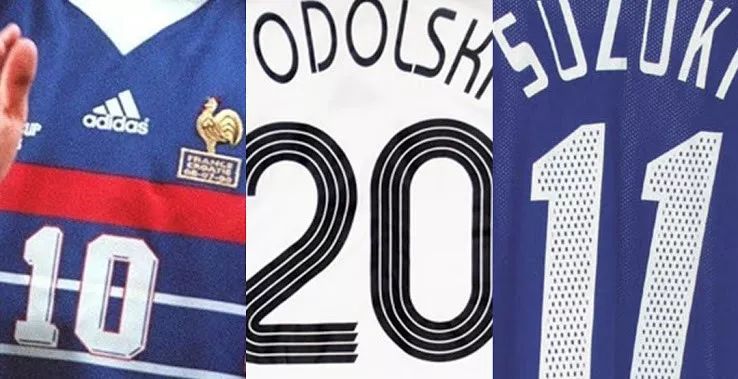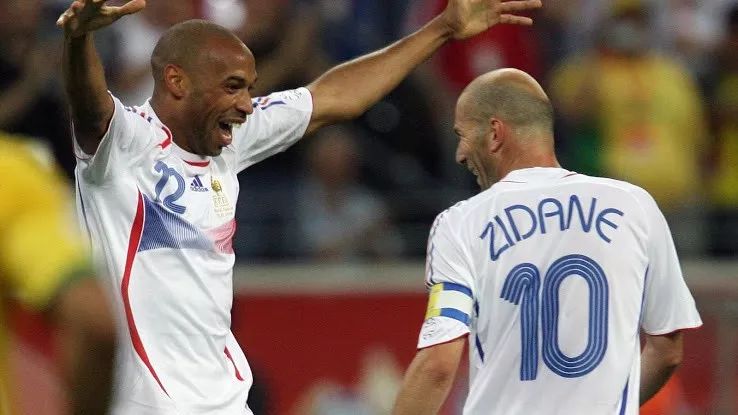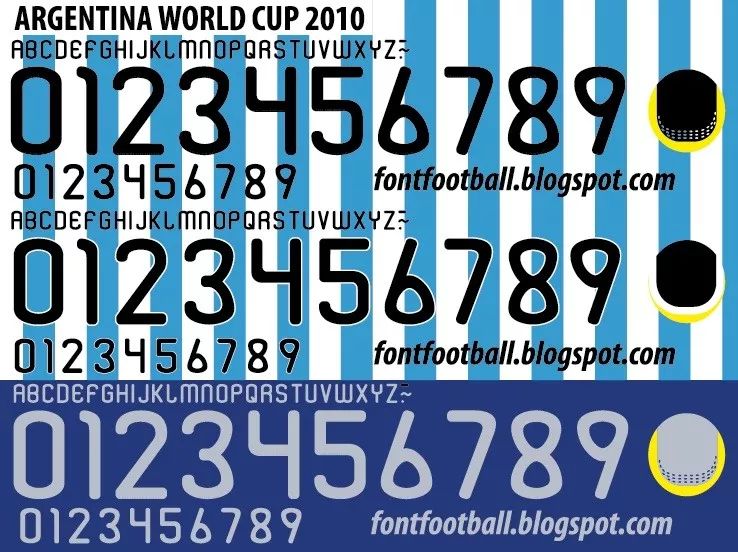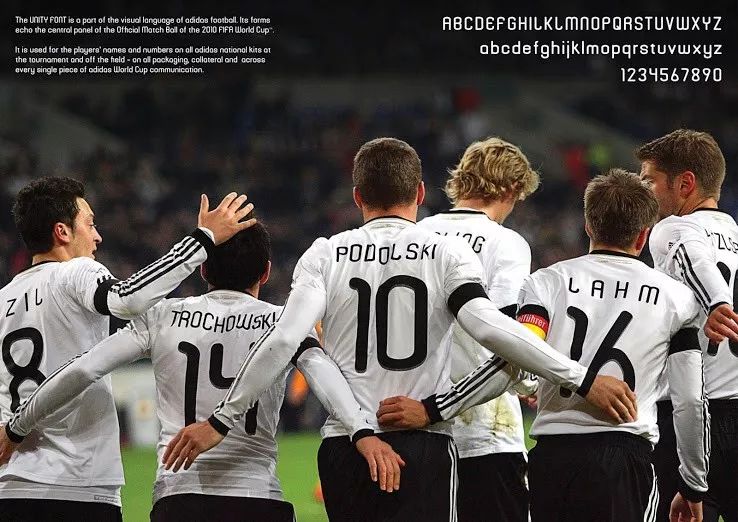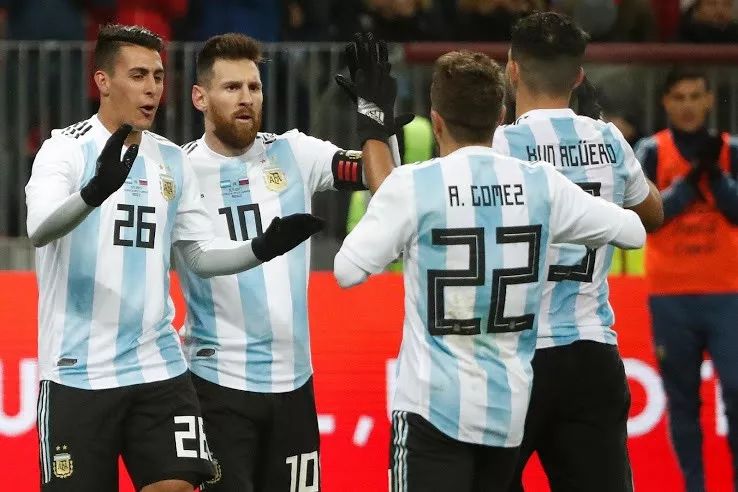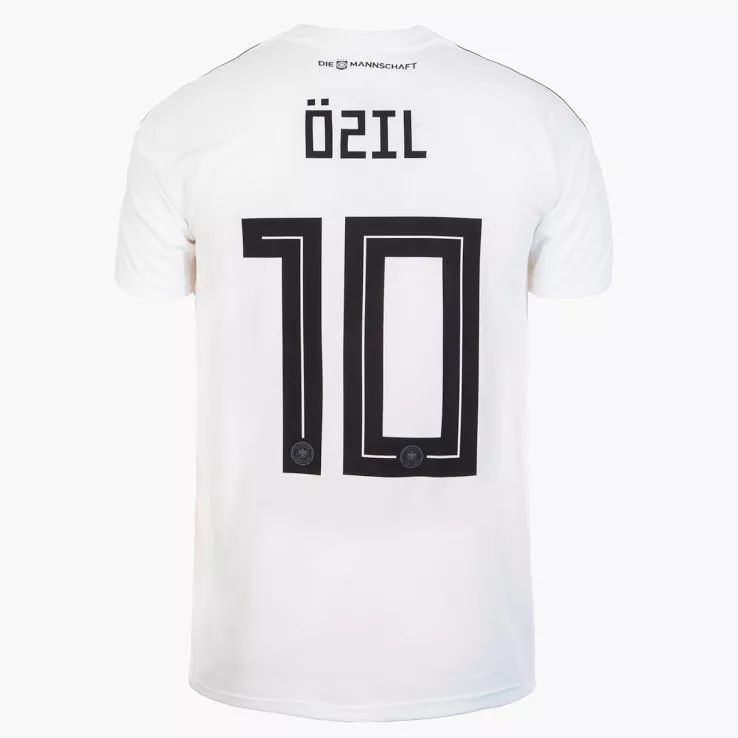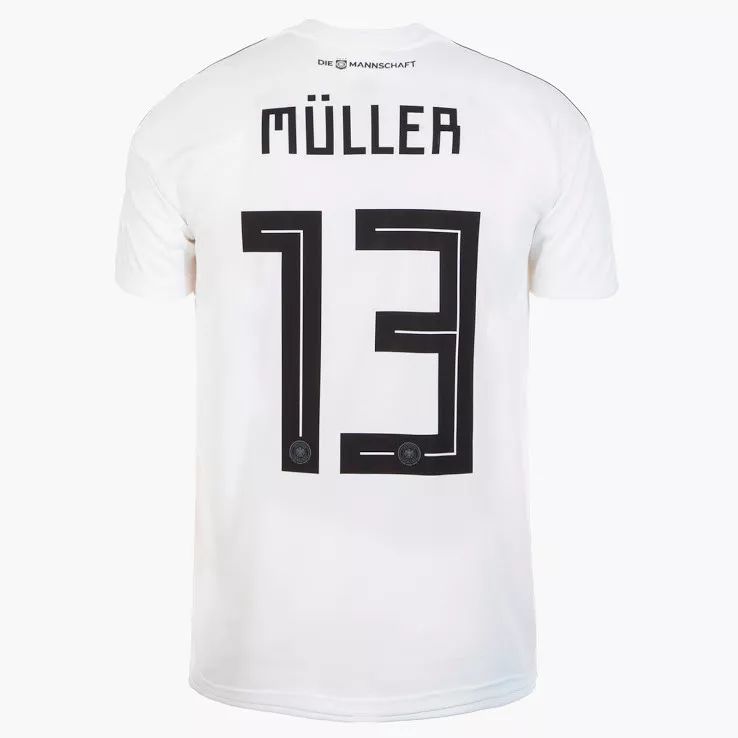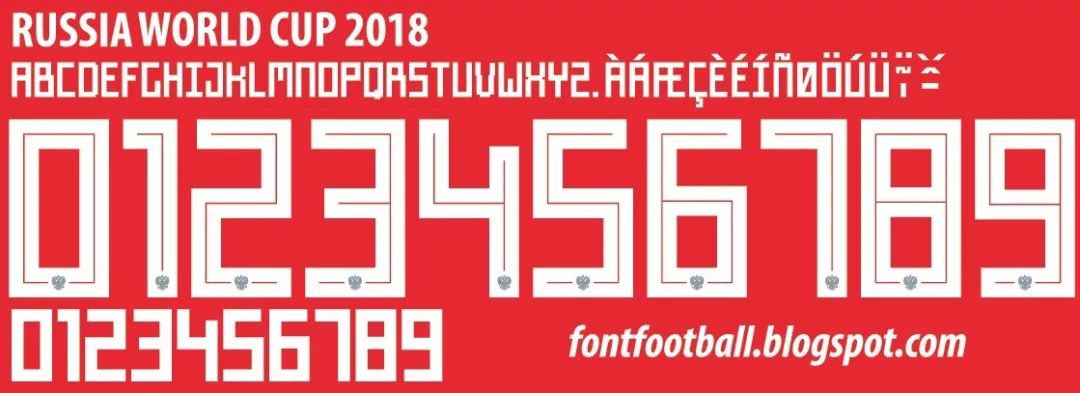
1990到2018年阿迪达斯推出的世界杯定制字体合集
各大品牌除了通过LOGO区分自己的赞助球队以外,球衣上的字体设计就是最大的区别了。
今天我们不妨回顾一下1990到2018年阿迪达斯推出的世界杯定制字体。
阿迪达斯1990年意大利世界杯
字体是一个概念非常单纯的3D风格字体。
阿迪达斯1994年美国世界杯字体
本届世界杯大部分球队使用的字体和1990年一样,阿根廷队和西班牙队使用的字体和阿迪达斯赞助的其他国家队有所不同。
作为东道主的美国还是得到了阿迪达斯为他们专门定制的字体。
阿迪达斯1998年法国世界杯字体
大部分球队的字体依然没有改变,除了德国和西班牙。
阿迪达斯2002年日韩世界杯字体
一改往年常态,2002年日韩世界杯的阿迪达斯赞助球队启用了一套全新的现代设计。与1998年世界杯相比,这种焕然一新的字体面貌给观众们留下了非常深刻的印象。
阿迪达斯2006年德国世界杯字体
这款设计灵感源自于1974年世界杯的字体可谓世界杯设计的一代经典,是迄今为止知名度最高的世界杯定制字体。
阿迪达斯2010年南非世界杯字体
相比于上一届字体的成功,2010年阿迪达斯世界杯字体要不起眼很多。设计概念是和当年的世界杯视觉主题一致。
阿迪达斯2014年巴西世界杯字体
2014年的世界杯字体造型现代,个性独特。
阿迪达斯2018年俄罗斯世界杯字体
今年阿迪达斯首次决定给各队的号码下方增加他们的国家纹章,让这些国家队的号码看起来都更有个性。